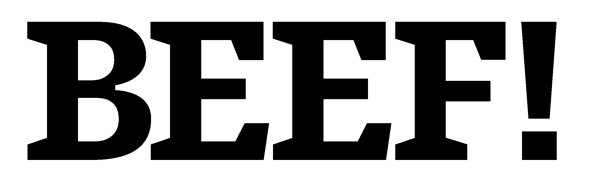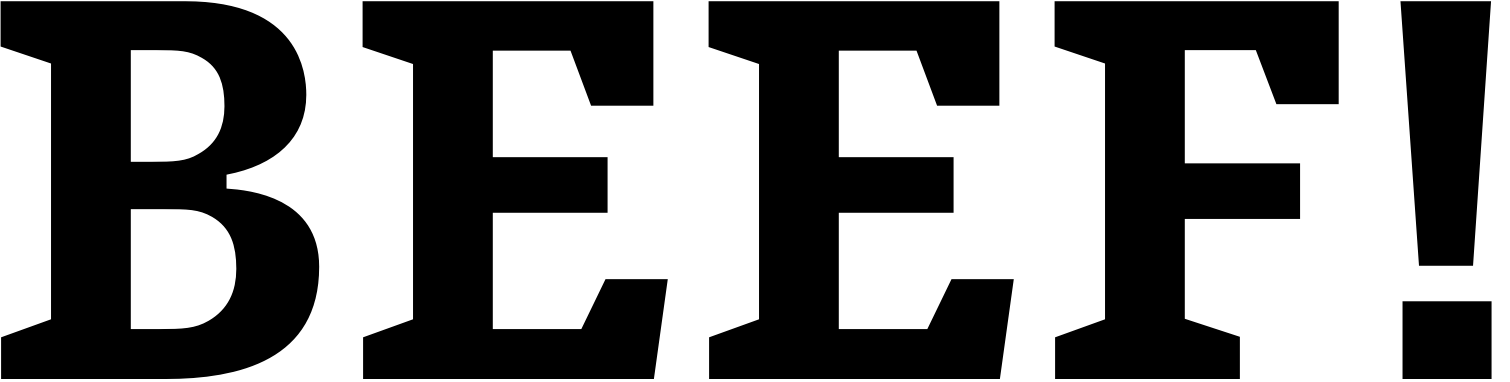
Logoschrift von BEEF gesucht …
Sie verwenden ja die Caecilia als Headlineschrift – wurde das Logo eher aus dieser entwickelt oder ist das eine eigene Schrift?
Hast Du die Caecilia mal testweise darüber gelegt? Nach mein Empfinden hat man sie (möglicherweise sogar nach dem Vorbild der TheSerif) weiterentwickelt. In der PDF ist diese Wortmarke (als einziges Textelement) auch in Zeichenwegen dargestellt – aber das will nichts heißen.
Merkwürdig dass der mittlere Querstrich beim F nicht mit dem E übereinstimmt bzw. auf einer Höhe liegt ...
Bei Schriften kenne und verstehe ich das. Bei einem Logo wie dem von BEEF wirkt es allerdings fehlerhaft zumal der Unterschied relativ klein ist. Wäre er deutlicher könnte ich eher damit leben ...
Ich musste im ersten Moment an die Guardian Egyptian von Christian Schwartz denken. Die kommt allerdings auch nur in die Nähe der gesuchten Logo-Schrift.
Was mich irritiert, ist die deutliche Tintenfalle im B. Das spricht meines Erachtens dagegen, dass die Schrift eigens für das Logo gezeichnet wurde. Stattdessen wird die Grundlage wohl eine existierende Satzschrift sein.
Ja, die irritierte mich auch. Da der Eintrag von bertel kam, bin ich davon ausgegangen, dass alle Softwarelösungen schon zum Suchen genutzt wurden … wie wäre es denn mit der FF Olsen? Die hätte dann auch (anders als die Caecilia) das eckige Ausrufezeichen:
Da der Eintrag von bertel kam, bin ich davon ausgegangen, dass alle Softwarelösungen schon zum Suchen genutzt wurden … wie wäre es denn mit der FF Olsen? Die hätte dann auch das eckige Ausrufezeichen